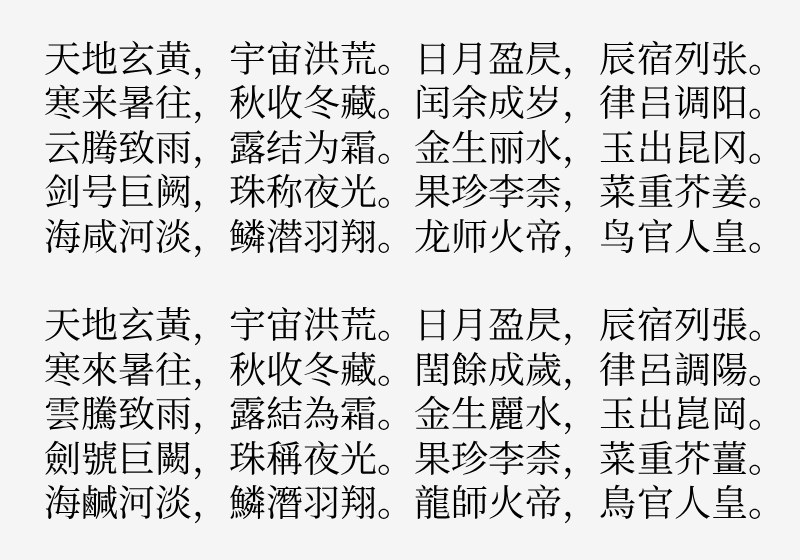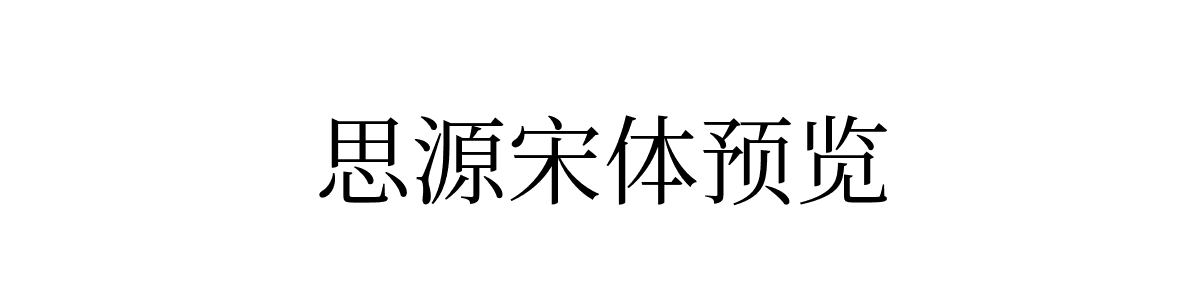
思源宋体
思源宋体(Source Han Serif)是 Adobe 与 Google 联合推出的开源宋体,作为思源黑体的对应版本,这款字体主要面向中日韩等亚洲语言设计,支持简繁中文、日文韩文,同时西文部分基于 Source Serif,也覆盖了拉丁、希腊及西里尔字母,多语言排版能力十分全面。
字体一共提供七种字重,整体汉字数量达到 458745 个,单一字重就包含 65535 个字形,字库规模庞大,几乎能满足各类专业排版需求。
字体风格
思源宋体字形端正,笔画平直硬朗,转折处处理得干净利落,整体结构稳重清晰。字体已针对屏幕显示做过专门优化,曲线简洁规整,显示效果锐利易读,实用性很强。
它既适合用于文学感较强的正文排版,也能胜任偏优雅、时尚的标题设计。在长篇阅读、多语言混排,或是需要体现专业、可靠形象的场景中,思源宋体都是适用性极强的选择。